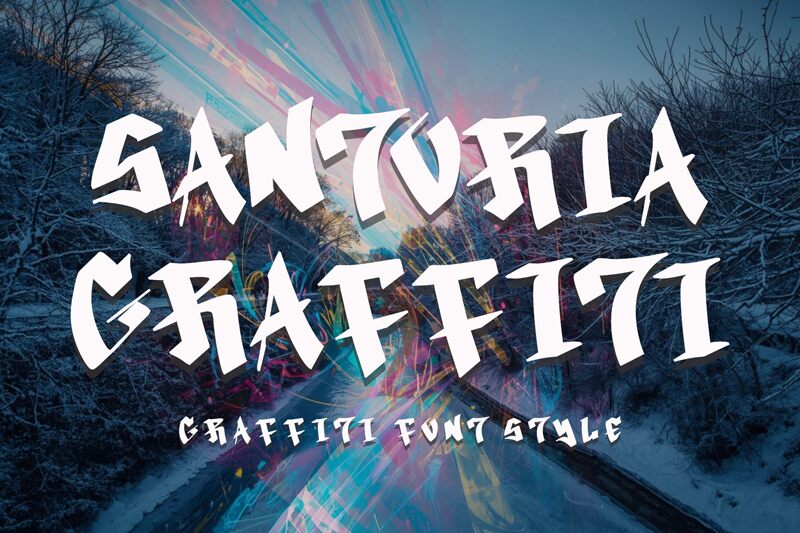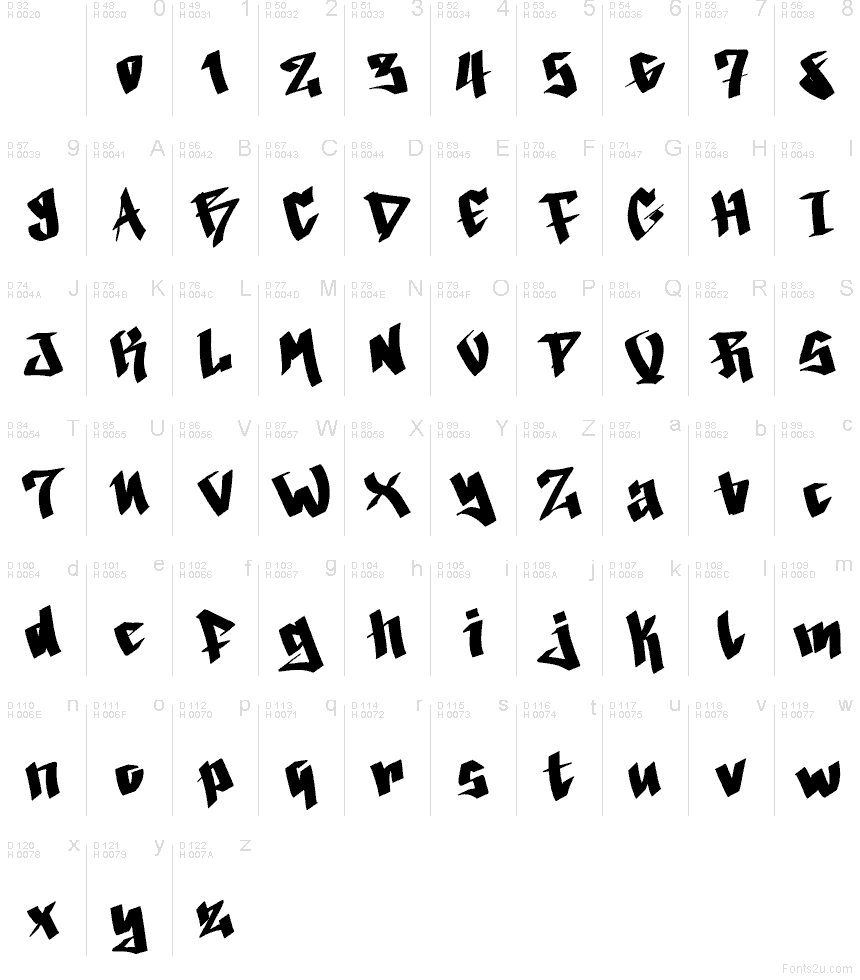
Santoria Graffiti Demo
Santoria Graffiti é uma fonte de graffiti gratuita, com traços afiados, cortes marcantes e um ritmo dinâmico escrito à mão. Suas letras apresentam ângulos pontiagudos, emendas abruptas e formas em cunha que conferem a todo o conjunto uma energia crua, típica da arte de rua, sem sacrificar a legibilidade dos caracteres.
Santoria Graffiti é perfeita para cartazes, capas de álbuns, branding de moda urbana, flyers, autocolantes e logotipos que exijam uma estética street-art. Esta fonte gratuita adapta-se facilmente a estas necessidades, pois as suas formas irregulares e cortes inclinados carregam uma forte identidade visual de graffiti, mesmo em frases curtas e layouts compactos.